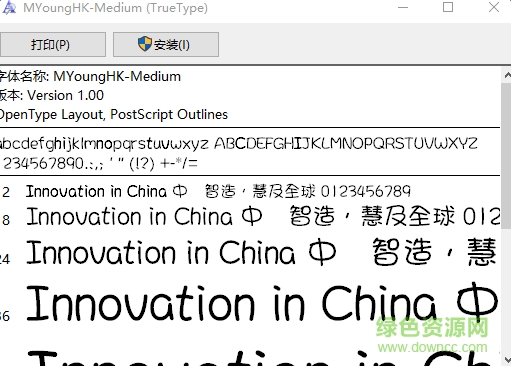
蒙納繁俏皮體是蒙納字庫中的一款繁體字體,這款字體寫出來的字是很好看的,不僅字形美觀、大氣,還很實用,可以用于很多方面,歡迎有需要的朋友來綠色資源網(wǎng)下載。
蒙納繁俏皮體確實是一款很不錯的電腦字體,小編也很喜歡這款字體,用于書畫上面題字題詞是很好看的,喜歡的朋友就快來綠色資源網(wǎng)下載吧。